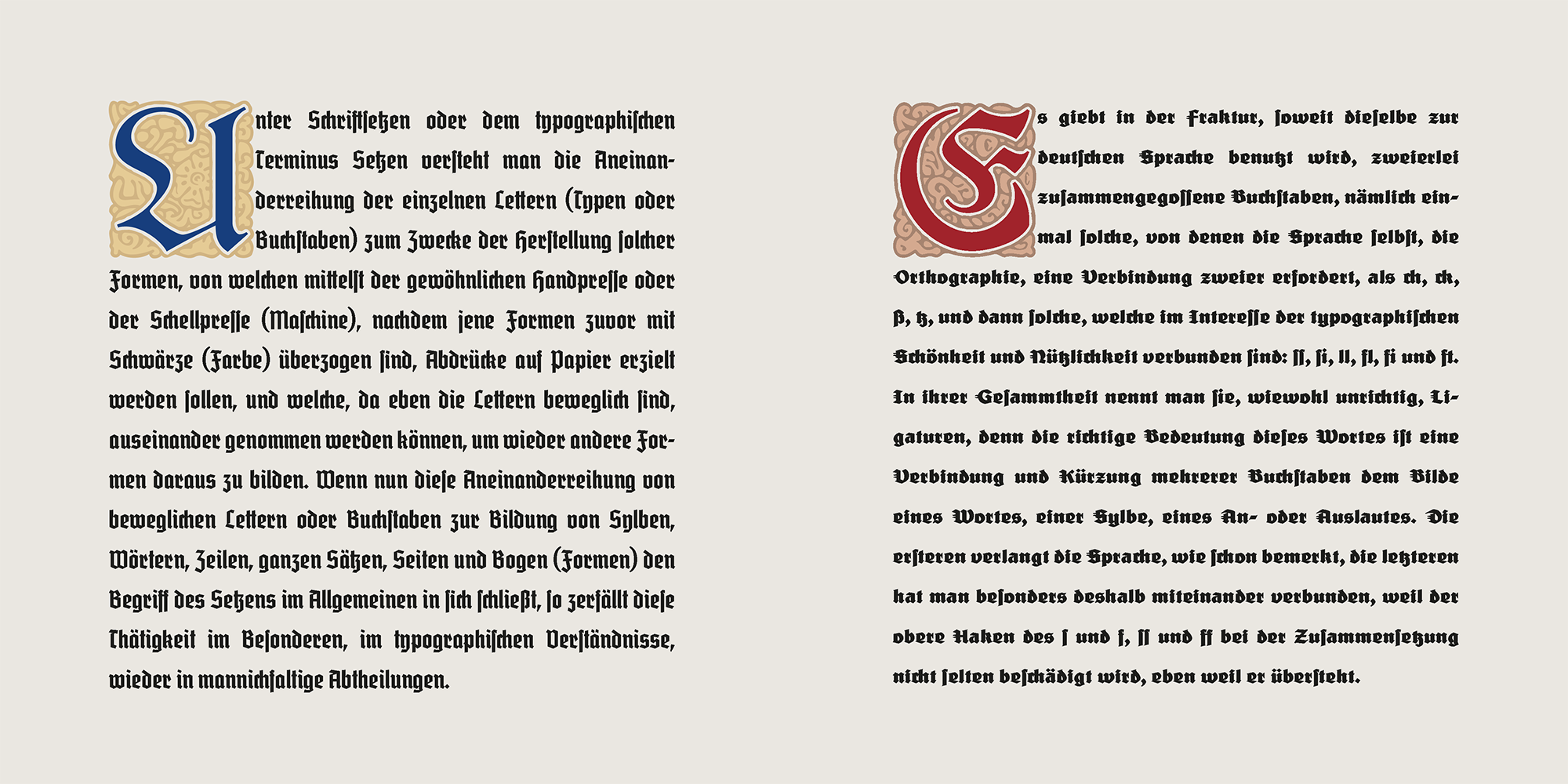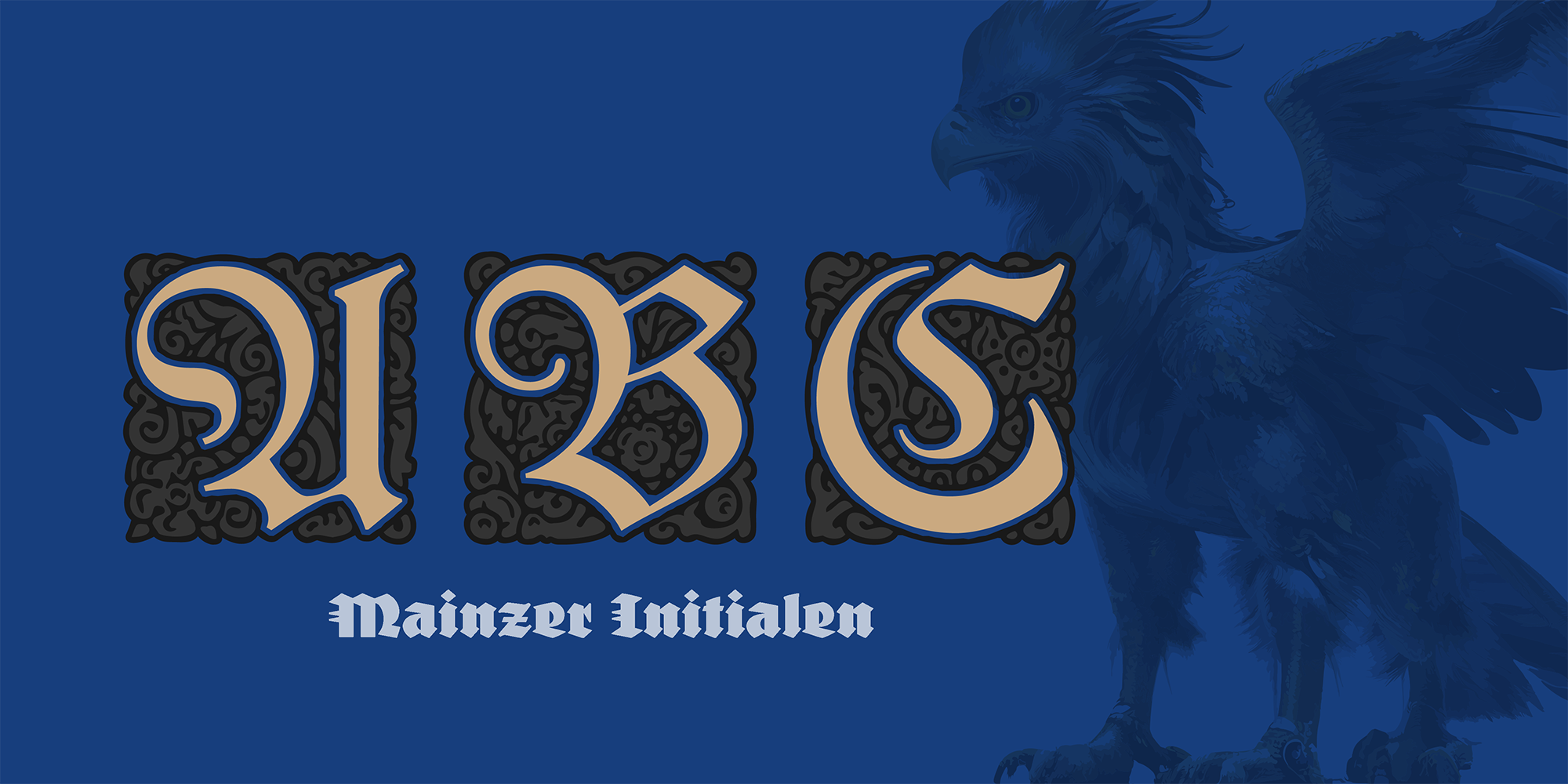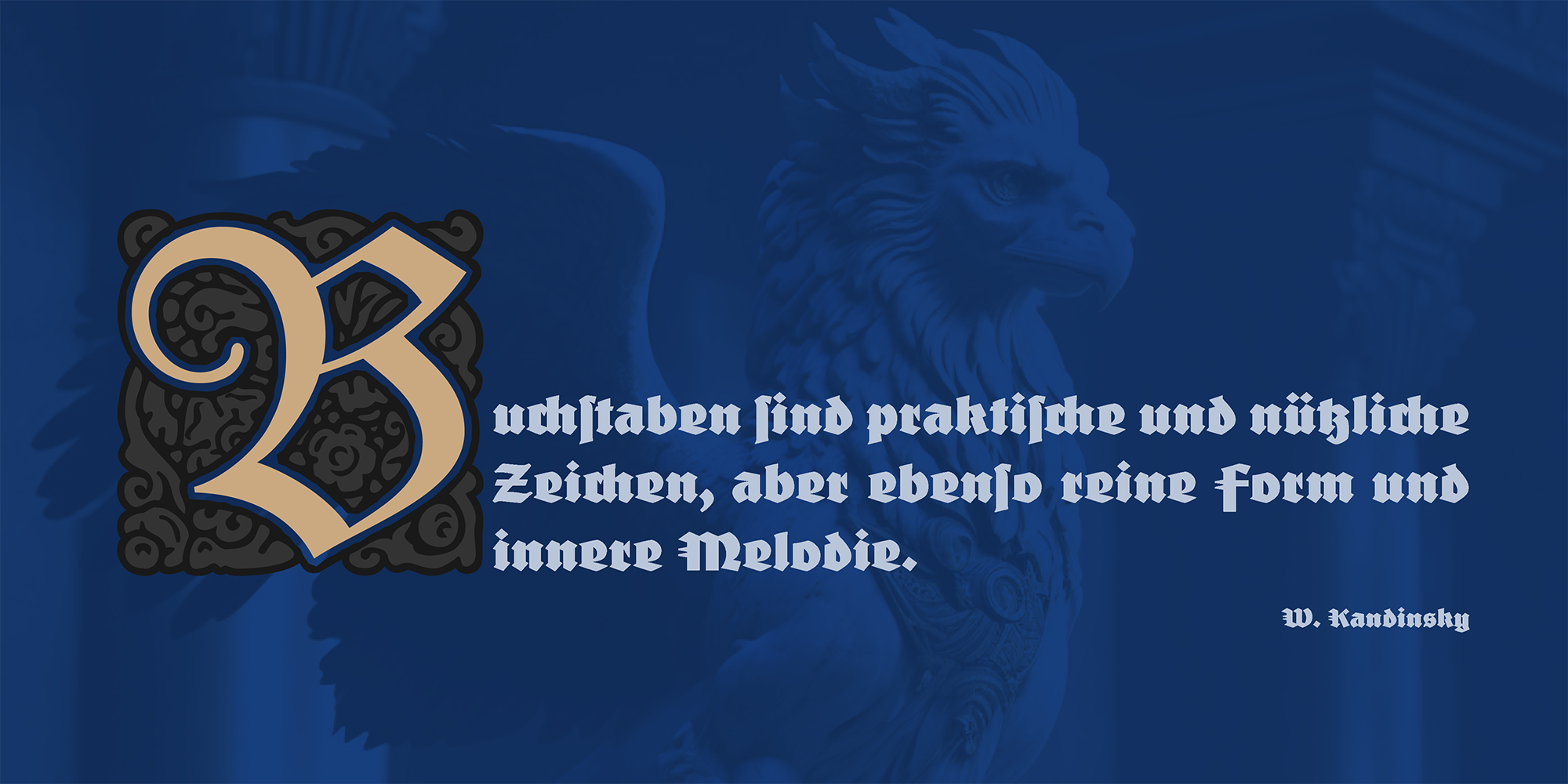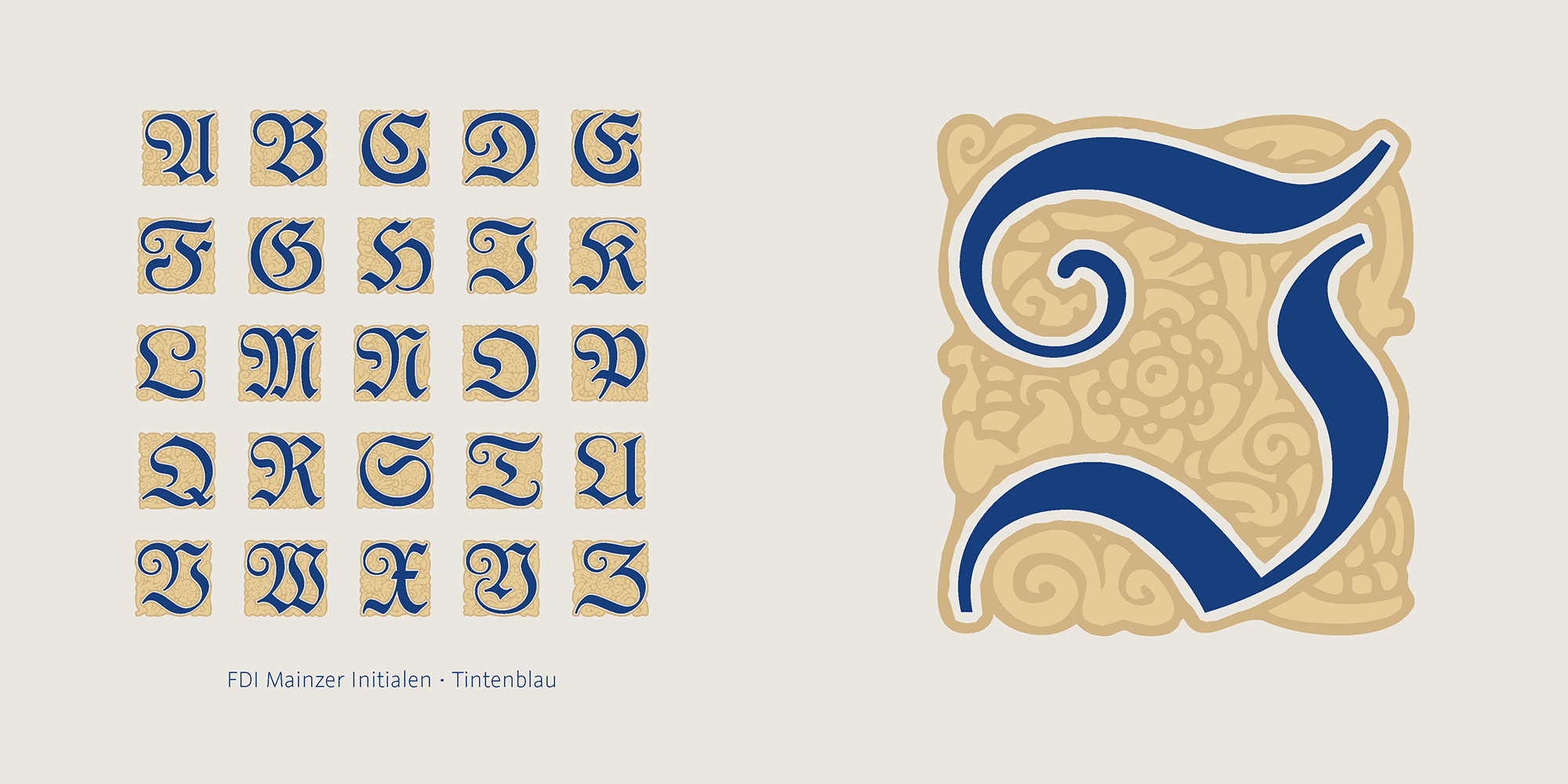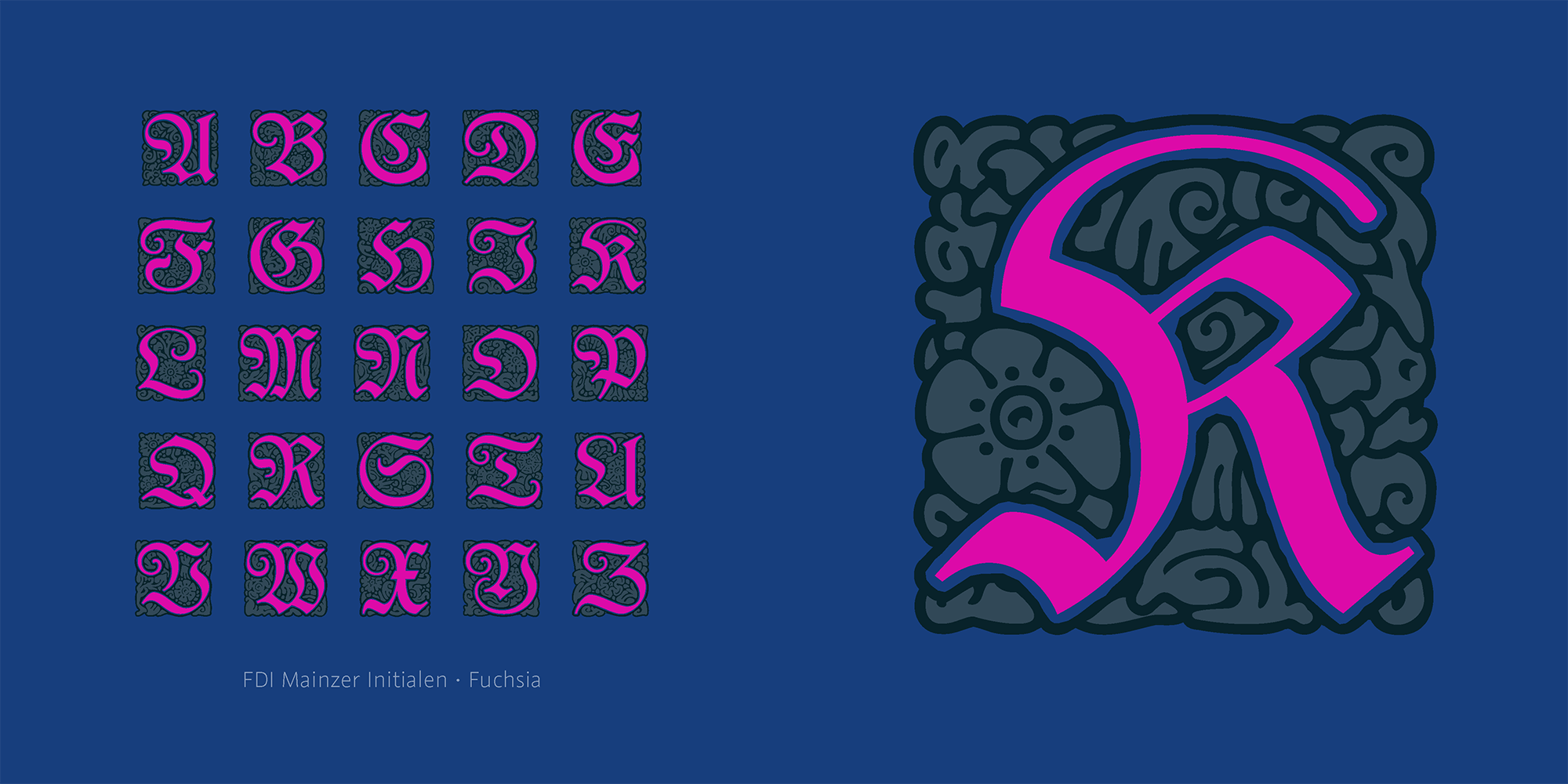
Font-Wiki: FDI Mainzer Initialen
Die FDI Mainzer Initialen ist eine Schrift, die die Initialen der Mainzer Fraktur als dreifarbige, digitale Schrift umsetzt. Nutzer der Schrift können auf zehn OpenType-SVG-Fonts mit vorbereiteten Farbpaletten zurückgreifen. Ein zusätzlicher Webfont im COLR/CPAL-Format ermöglicht den Webeinsatz mit den gleichen 10 Paletten oder beliebigen, per CSS einstellbaren Farben.